Las tipografías Palo seco, conocidas como sanserifas, son la antítesis de las tipografías romanas (serifas), pues presentan un estilo aparentemente limpio, funcional y aséptico, en contraste con los remates tan embellecedores y distintivos de las romanas, que daban una presencia única a cada tipografía.
No obstante, como vas a comprobar, al tener tan amplia variedad de matices y estilos, la asepticidad y monotonía que presentan las sanserifas, desaparece en muchos casos.
Características comunes en las tipografías Palo seco
En general, sus características formales son:
- La ausencia de modulación.
- La ausencia de Remates.
Podemos distinguir cuatro grandes variantes de Palo seco que van evolucionando desde un ductus caligráfico (humanista) hacia uno más sintético, más cuadrado y redondo (geométrico). Los cuatro tipos de palo seco características son:
Tipografías palo seco Grotescas
Se observa como su escritura se asemeja un poco a la romana antigua; presentan objetividad, ausencia de demostraciones personales y formas sólidas de aspecto neutro pero no tenían por si solas una presencia propia, eran demasiado inocuas, demasiado asépticas en conjunto.
- Trazo homogéneo.
- Caracteres estrechos.
- Ausencia de remates.
- Suelen llevar el nombre «Gothic» al lado.
Las grotescas más clásicas son la: News Gothic, Bell Gothic, Franklin Gothic, Letter Gothic.
Tipografías palo seco Humanistas
Siguen teniendo ese ductus caligráfico que le aporta ese aire tan tradicional en la modulación del trazo dando un toque propio a los caracteres. Sus características son:
- Persistencia en la Modulación del trazo.
- Ausencia de Remates.
Las humanistas más características son: Gill Sans (Eric Gill), Antique Olive, Eras (Albert Boton), Open Sans (Steve Matteson) y la Syntax.
Tipografías palo seco Neogrotescas
Ya se vislumbran cambios significativos en relación a la realización del trazo que es absolutamente homogéneo, pero los caracteres todavía tienen una concepción humanística.
Entre sus características tenemos:
- Ausencia de Modulación.
- Ausencia de Remates.
- Estructura humanística del carácter.
Las neogrotescas más características y difíciles de distinguir entre ellas son: Frutiger (Adrian Frutiger), Helvetica (Max Miedinger), Univers (Adrian Frutiger), Arial y Myriad Pro.
Algunas diferencias entre las Neogrotescas
Yo te muestro algunas diferencias entre las serifas neogrotescas. Como podrás apreciar, las diferencias son sutiles:
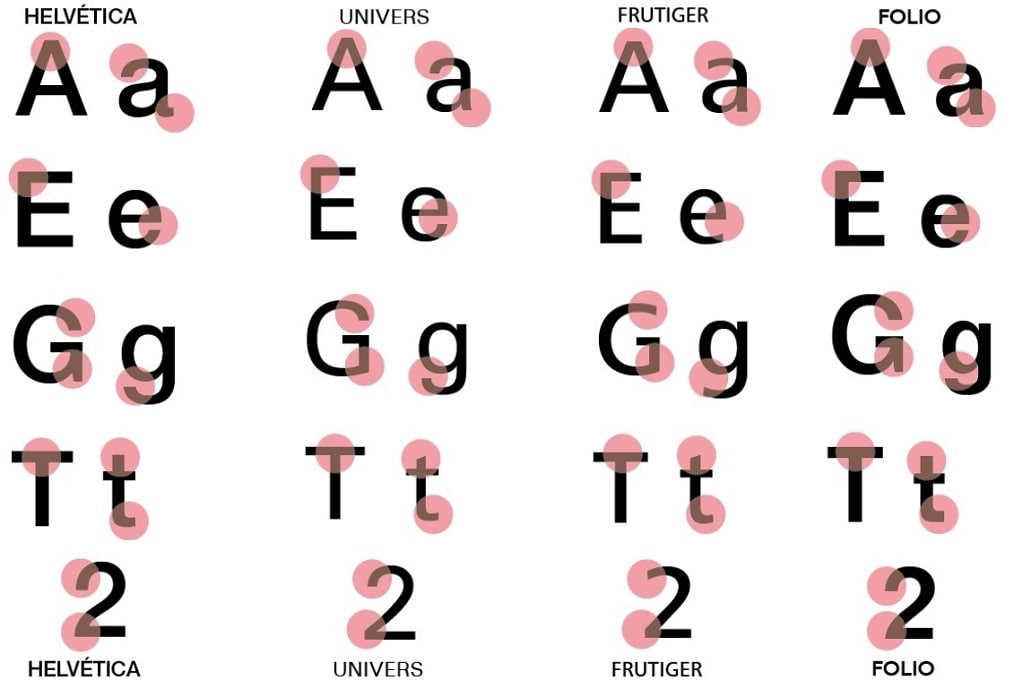
- Arial vs Helvetica
- Helvética vs Univers (track)
- Frutiger vs Univers
- Frutiger vs Myriad (muy similares)
Tipografías palo seco Geométricas
No solo es que la realización del trazo es absolutamente homogénea, sino que además los caracteres acaban teniendo una concepción geométrica; esto origina un Ductus más sintético, mas redondo y más cuadrado.
Entre sus características tenemos:
- Ausencia de Modulación.
- Ausencia de Remates.
- Estructura Geométrica del carácter.
Destacan las Avant Garde, Futura (Paul Renner), Avenir (Adrian Frutiger), Bank Gothic, Century Gothic (Morris Fuller), y la particular Kabel (Rudolf Koch).
Detalles de la Futura (Paul Renner)
Dado que es la tipografía que más me gusta de entre las sanserif, sería bueno poder dar detalles del porqué, y es que la tipografía creada en el 1927 por Paul Renner es una tipografía que presenta todas las propiedades de una palo seco geométrica: Proporcionalidad perfecta de sus caracteres, y una estructura geométrica perfecta del carácter; es en definitiva y bajo mi punto de vista la que mejor define la característica fundamental de la tipografía palo seco: pasar desapercibida en su conjunto (aunque es cierto que caracteres como la «M» tienen el vértice con más altura que la propia linea de altura de las mayúsculas).
Fijaos en su Anatomía:
Y en su Simetría:
No es extraño pensar que al Dr. House le guste este tipo de letra también ¿verdad?
Palo seco Atípicas
Se pueden englobar a numerosas familias que siguiendo las características generales de las palo seco, no cumplen estrictamente con las específicas de los cuatro tipos de palo seco existentes, y que precisamente por esto, deberían ser englobadas dentro de la tipografía de fantasía.
Hay muchos tipos como por ejemplo: Eurostile, Kabel, Peignot, Bauhaus…
- La tipografía Eurostile parece geométrica pero no llega a darle esa concepción completamente a sus tipos.
- La tipografia Bauhaus es un ejemplo de una seudogeométrica que aunque sí tiene los caracteres geométricos no acaba cerrando algunos caracteres lo que le confiere un toque más fantasioso que geométrico.